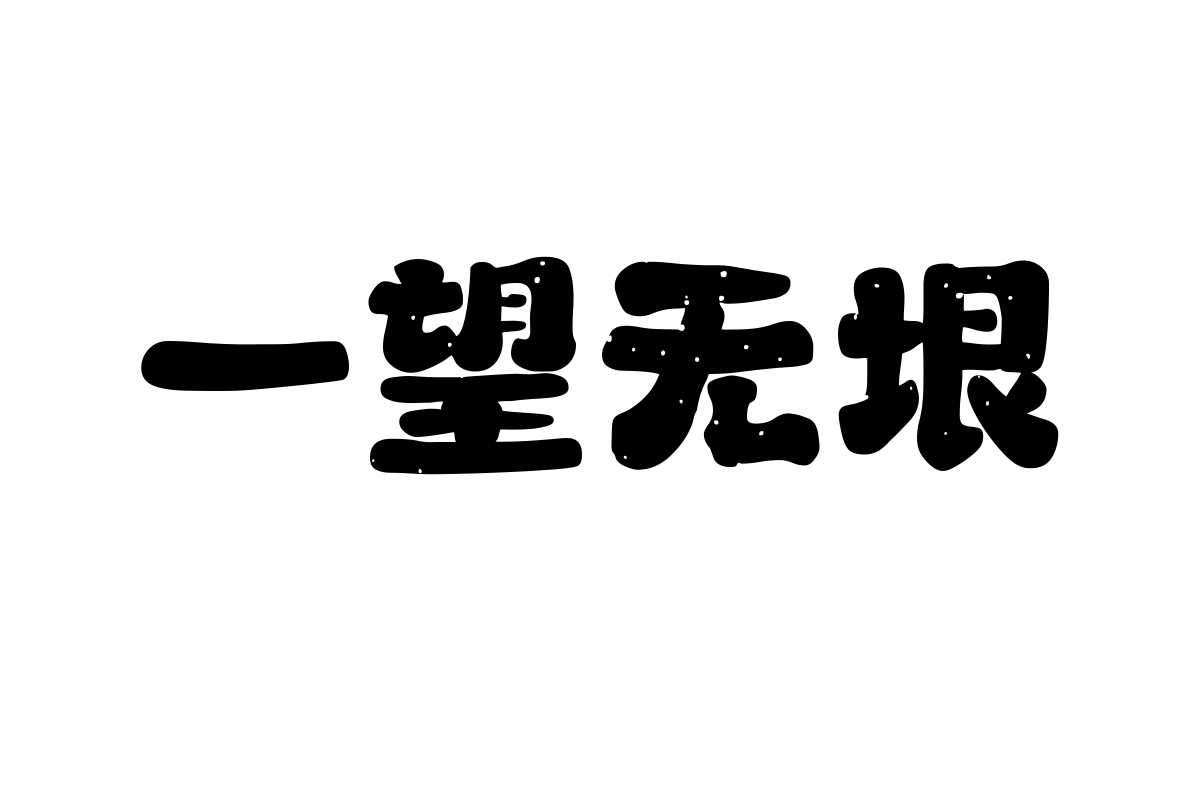
山海甜心曲奇w是一款字体,它的特点是具有可爱的风格和独特的造型。这款字体采用了圆润的线条和柔和的色彩,给人一种温馨而亲切的感觉。它的造型独特,线条流畅自然,仿佛是一颗颗甜蜜的糖果在纸上跳跃,让人忍不住想要品尝。
这款字体适用于各种与甜食相关的设计,如甜品店、蛋糕店、糖果店等,能够为这些场所增添一份甜美的氛围。同时,也适合用于个人博客、社交媒体、网络名片等场合,展示出自己的个性和品味。